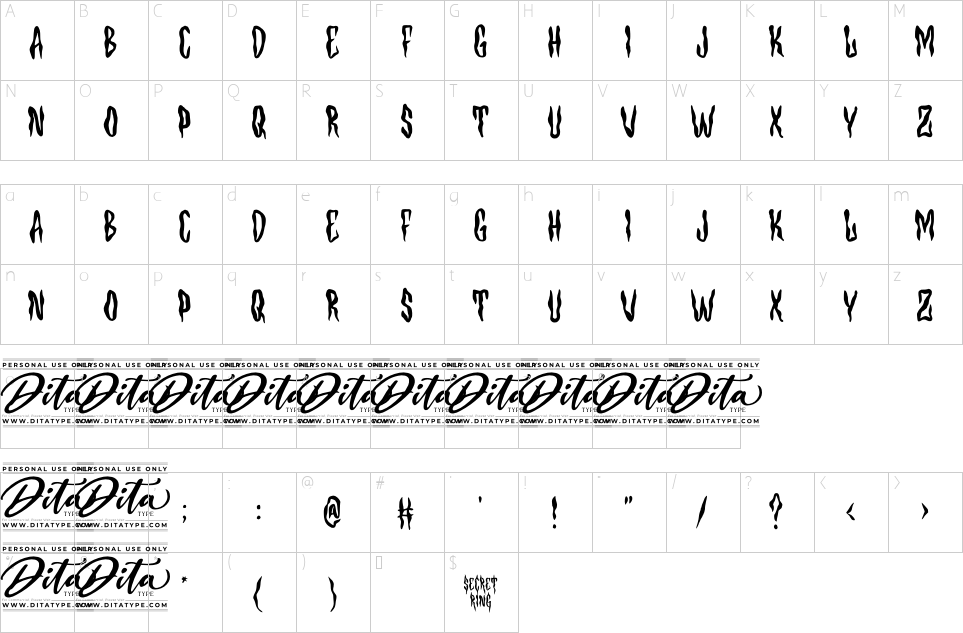
Secret Ring Font | 1001 Free Fonts – Download Grátis
A fonte ‘Secret Ring’ é uma elegante escolha para qualquer projeto visual, oferecendo uma aparição única e sofisticada que combina facilmente com vários estilos. Desenvolvida pela equipe da Dita Type, a font é especialmente adequada para criações digitais. Com seus detalhes meticulosamente criados, ‘Secret Ring’ é perfeita para textos de destaque ou subtítulos, proporcionando um toque criativo a qualquer layout. Sujeitamente popular, a font foi baixada 512 vezes, indicando seu valor como recurso gráfico de alta qualidade. Se você está procurando por uma fonte única e atemporal para seu próximo projeto, ‘Secret Ring’ certamente merece uma olhada. Descubra por si mesmo a sofisticação de ‘Secret Ring’.